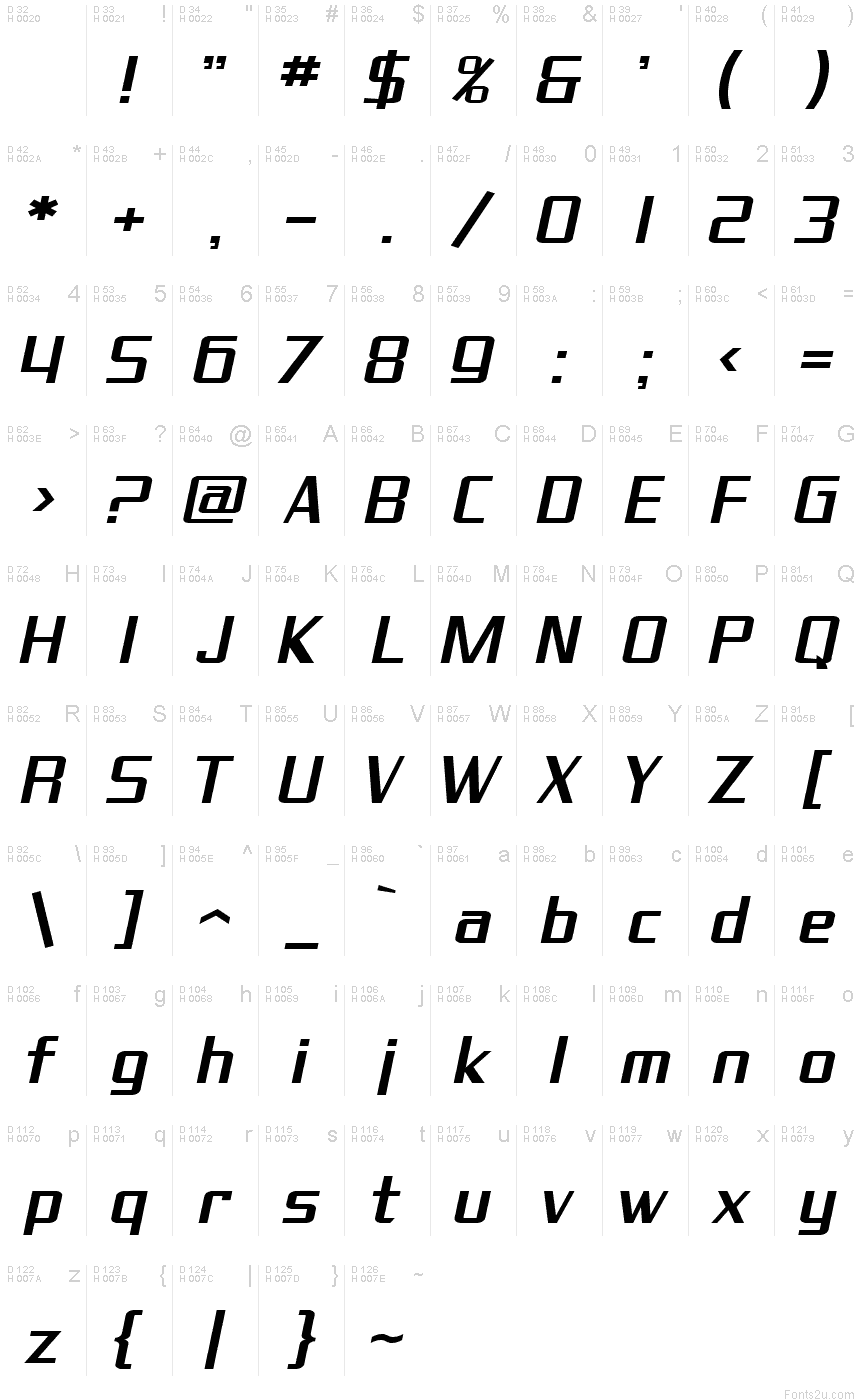
SF Theramin Gothic Oblique di ShyFonts Type Foundry è un font display moderno, gratuito e in stile techno, con quel taglio sci-fi veloce tipico della fine degli anni '90. I tratti ampi, gli angoli smussati e le barre trasversali basse donano alle lettere un aspetto aerodinamico e meccanico, mentre la decisa inclinazione spinge il design costantemente in avanti.
È ideale per loghi di videogiochi, flyer di musica elettronica, titoli di poster, branding ispirato alle interfacce utente e copertine di riviste, dove un font gratuito veloce aiuta a dare il tono giusto. Funziona al meglio nelle impostazioni display brevi, poiché le forme angolari e i tagli netti esprimono al meglio il loro carattere quando il lettering ha lo spazio per apparire audace e direzionale.